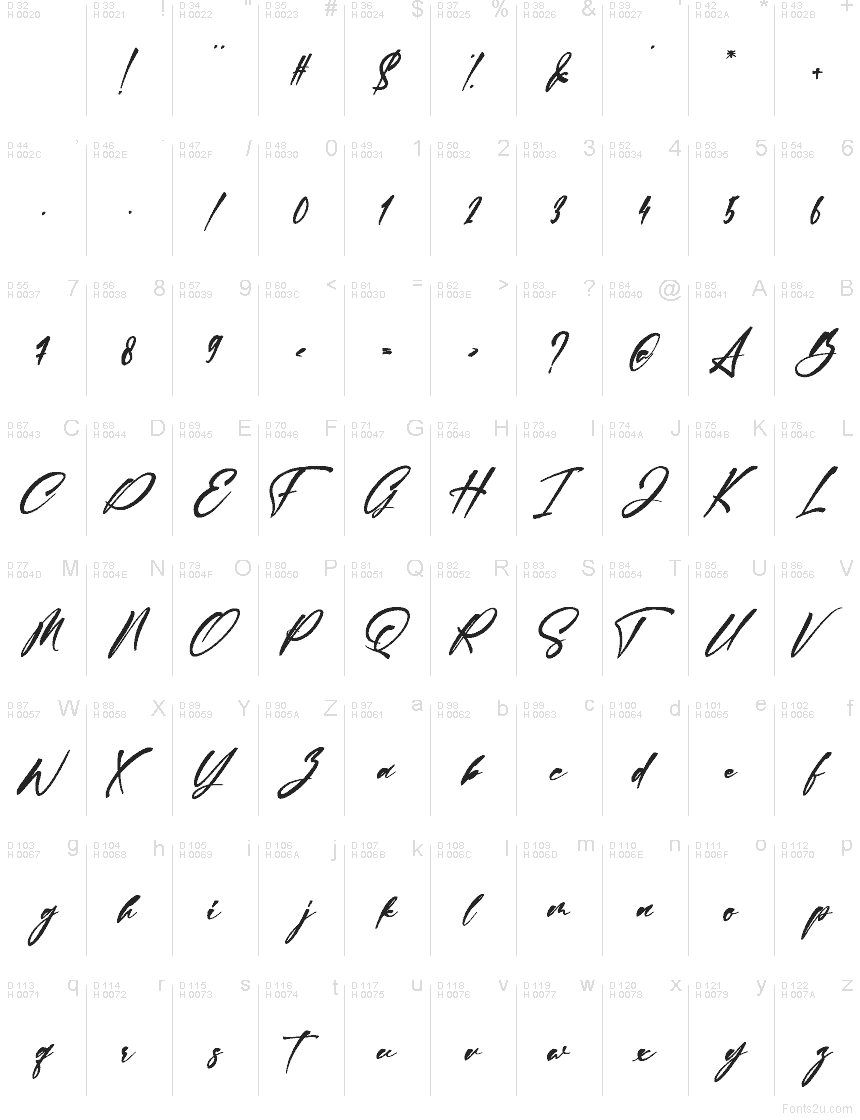
Balonesti od Pineungtype je bezplatné psané písmo inspirované dlouhými, rozmáchlými tahy štětce a rychlými změnami směru, díky nimž působí písmena spíše spontánně než příliš uhlazeně. Vysoké smyčky a ostře zúžené tahy mu dodávají tempo podpisu, přičemž opakující se pohyb zajišťuje vizuální soudržnost celé sady.
Tato energie vynikne zejména u log butiků, obalů produktů, citátů na sociálních sítích, pozvánek na akce či brandingu kaváren, kde osobní projev přebíjí strohou formálnost. Písmo může také skvěle posloužit jako hlavní prvek v krátkých plakátových nadpisech nebo u návrhů etiket, zejména pokud chcete, aby celou kompozici nesl rychlý pohyb štětce.